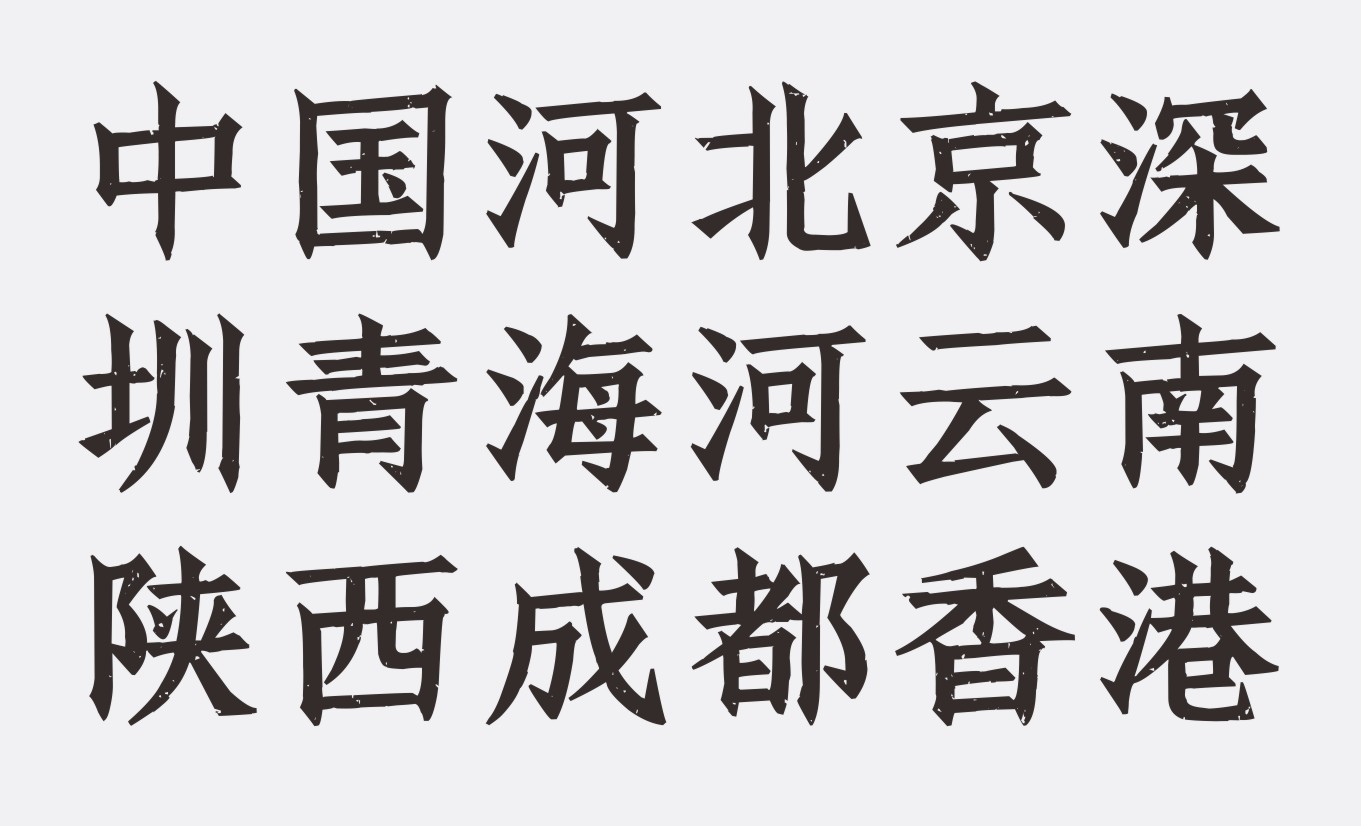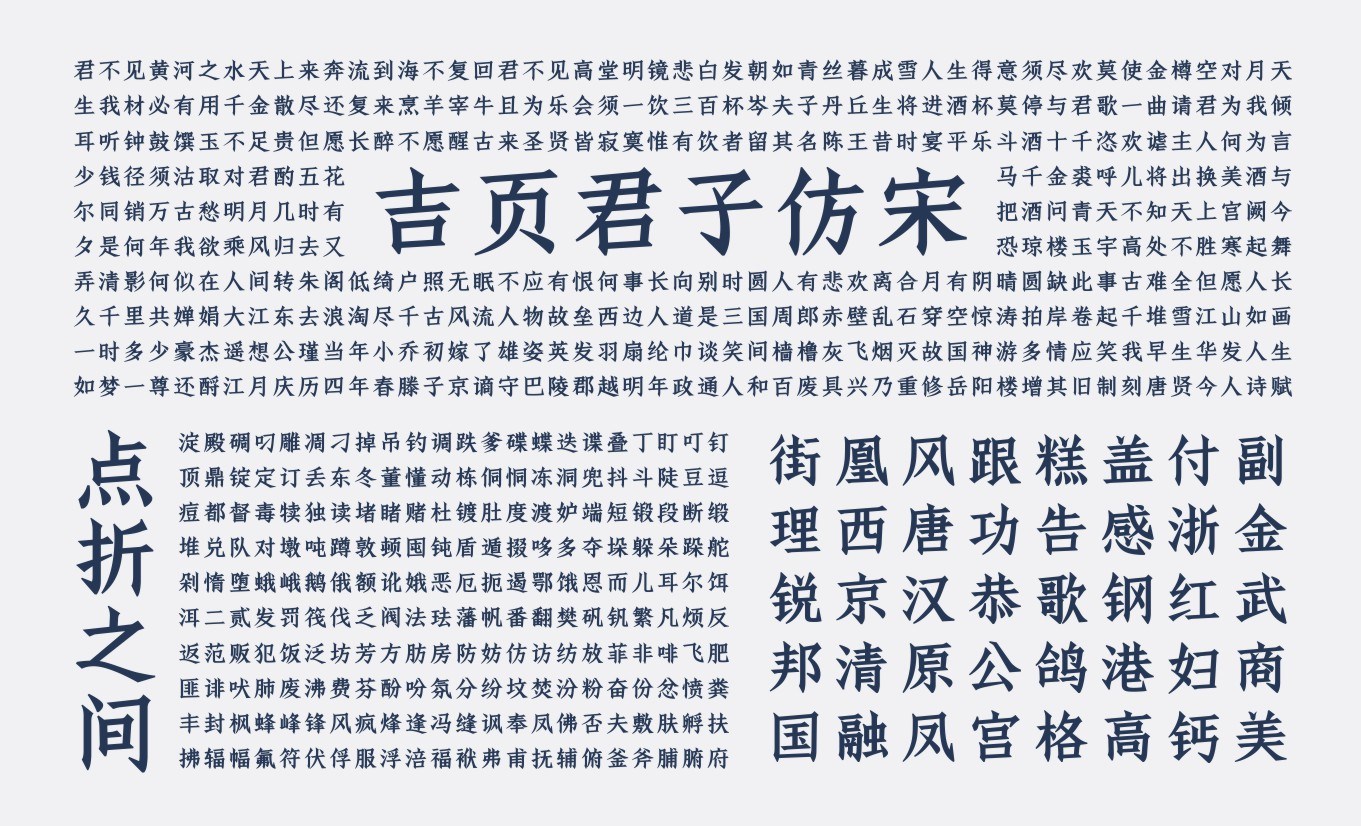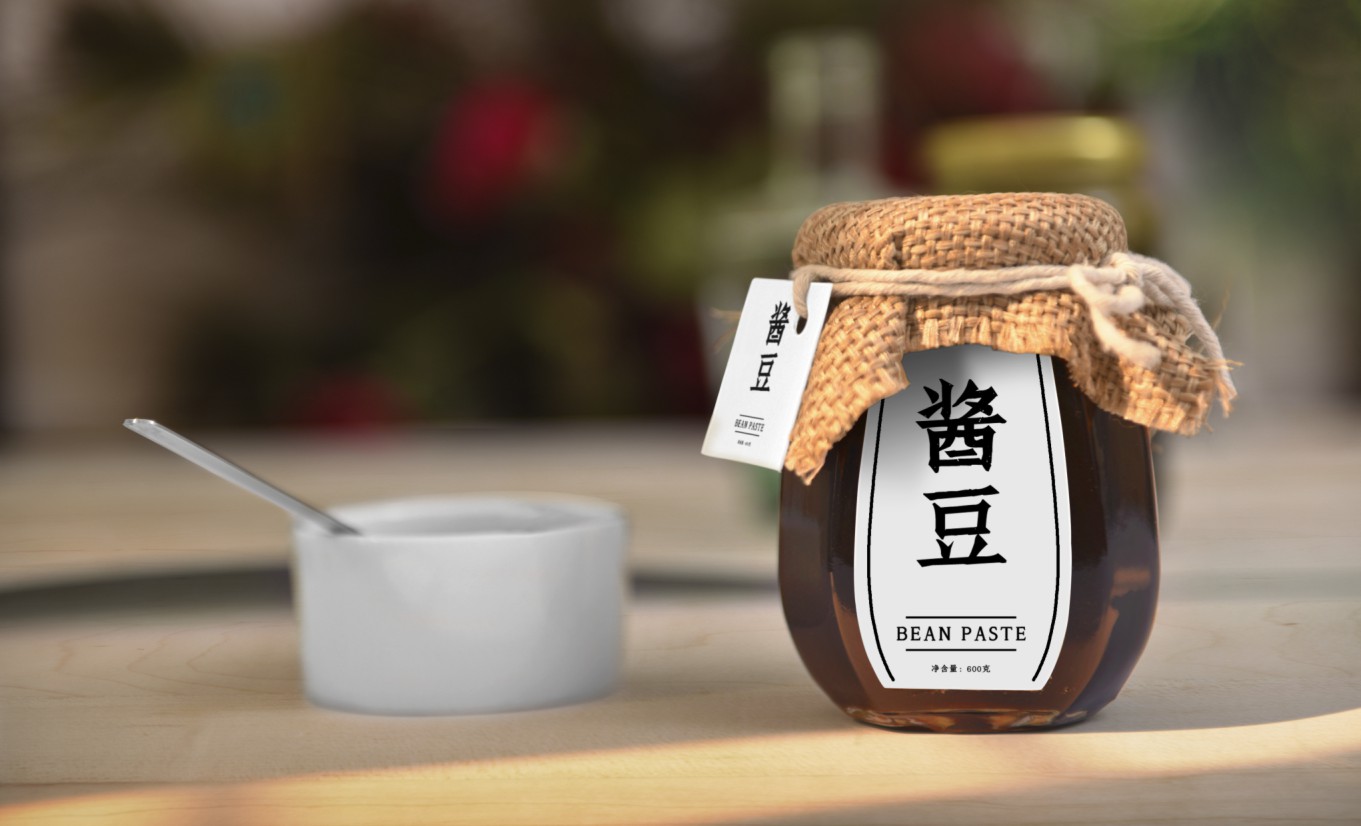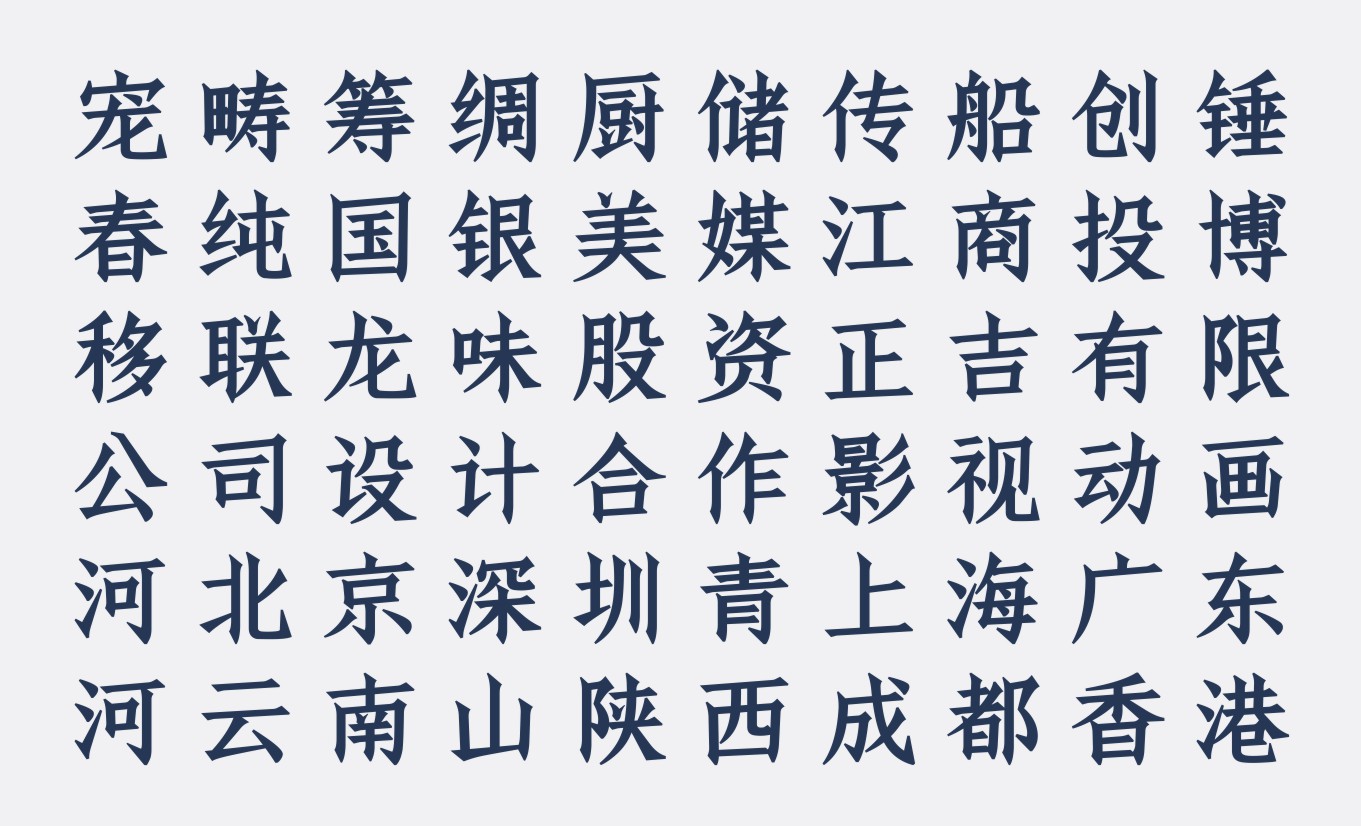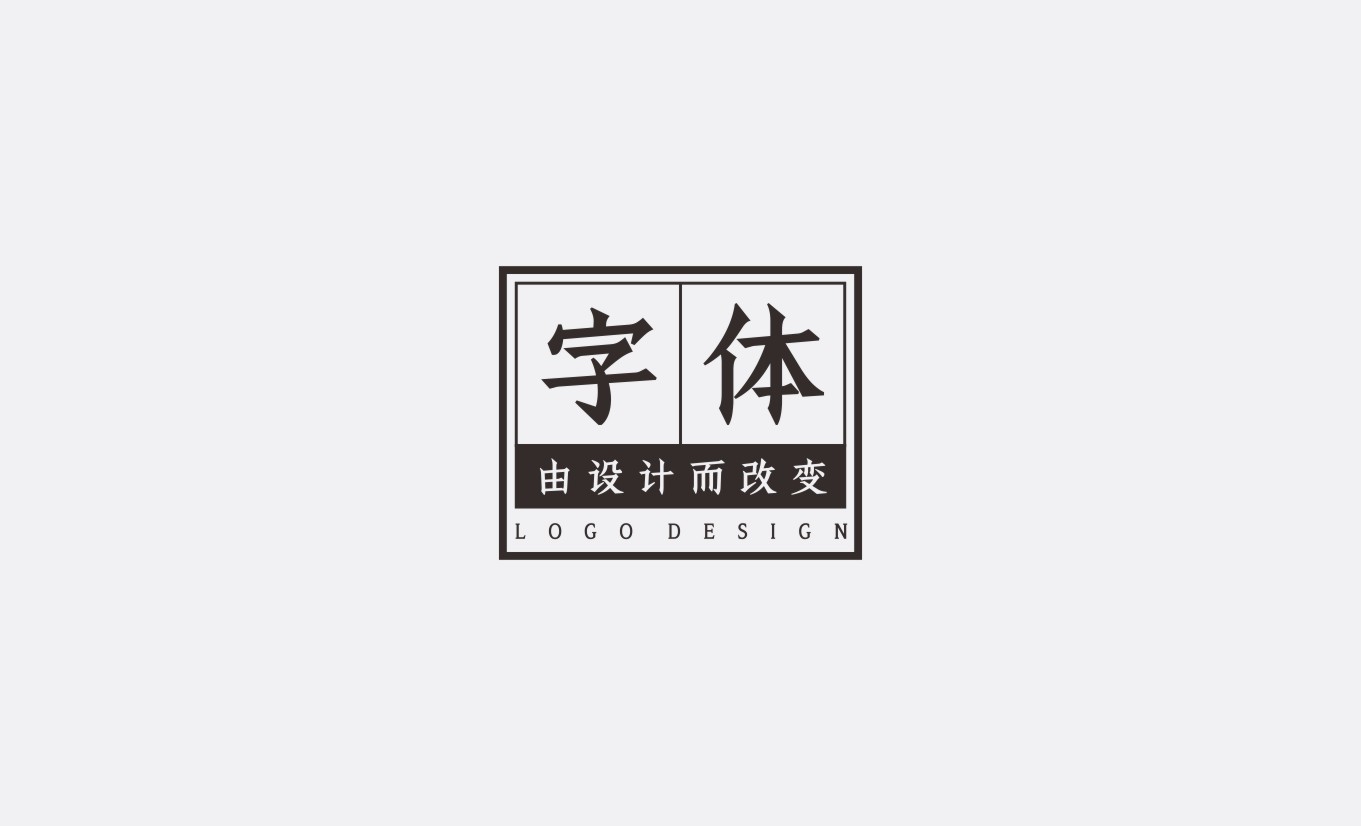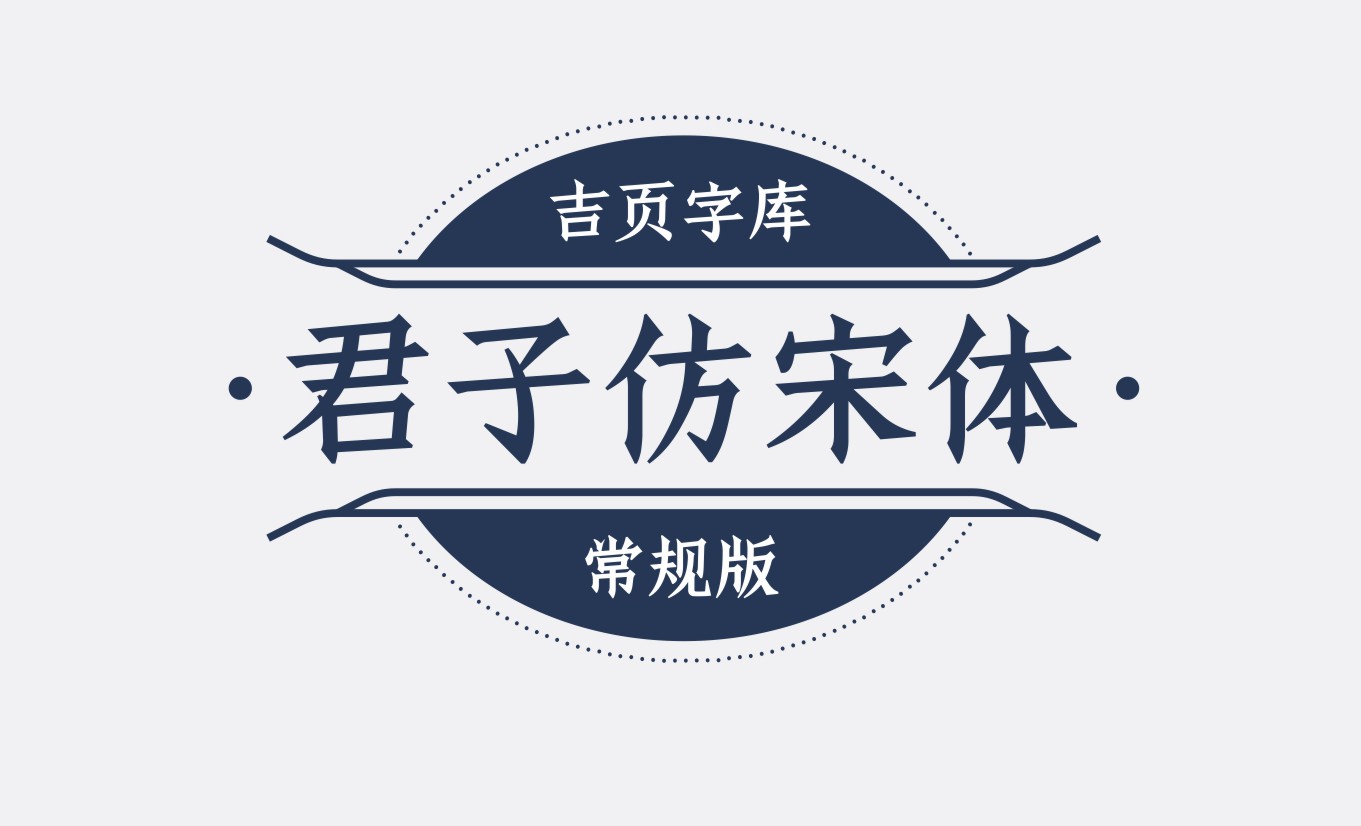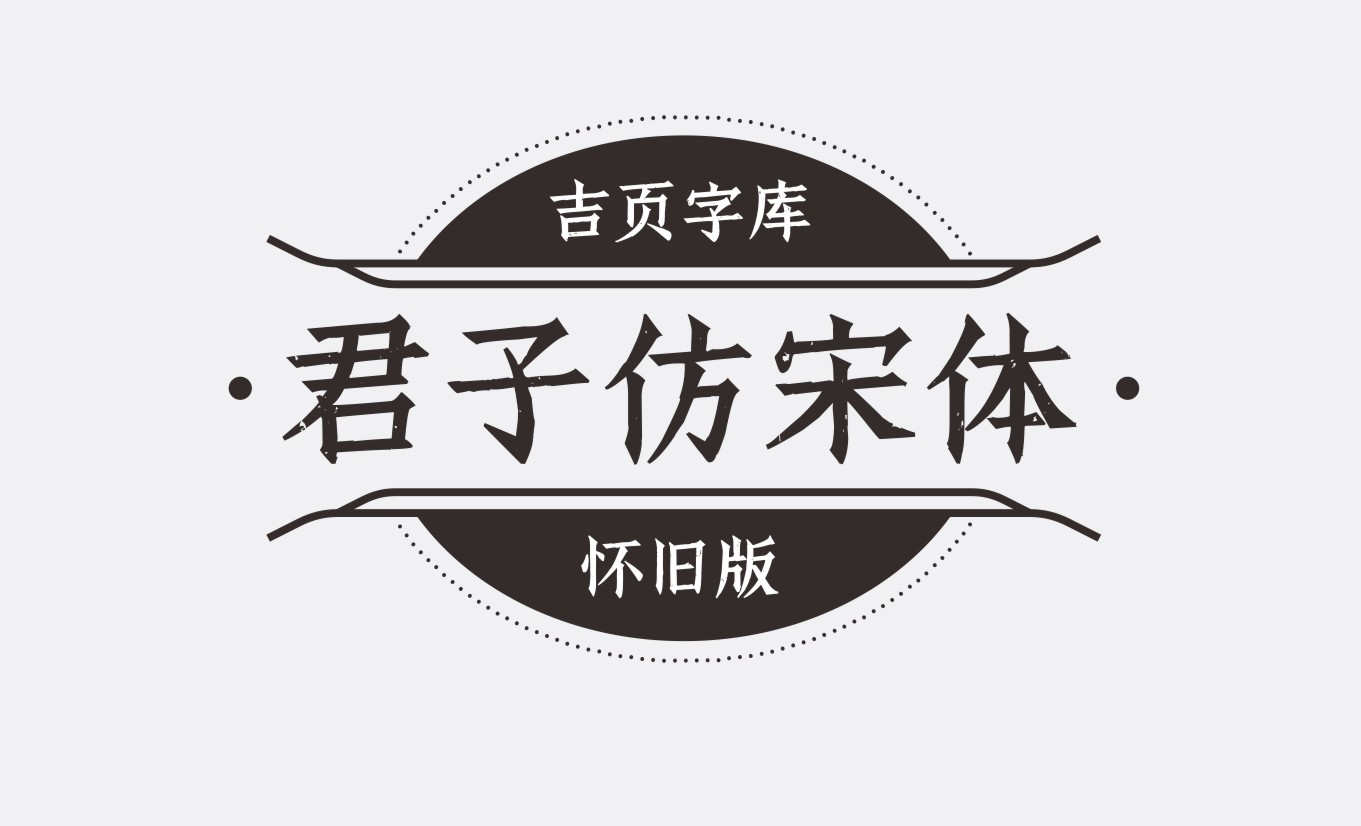
吉页君子仿宋体上线了
首先说一下为何叫“吉页君子仿宋体简”体。因为此款字体为粗仿宋,但鸡哥觉得粗仿宋这个名字较为普通,而吉页君子仿宋体在风格上没有什么浮夸的装饰性元素,笔笔坦荡,字字稳重,故视为君子。 目前市场上粗仿宋稀缺,为此,吉页字库为粗仿宋填补了一下坑。虽然是微不足道的一抹,还请各位为鸡哥点点赞,转转发。 吉页君子仿宋体简在GB2312的基础上增加了148个汉字,共计6911个汉字,大小写西文、数字及常用符号。 此外,吉页君子仿宋体简还做的一版“怀旧版”,以便不同场景的应用。
吉页君子仿宋体上线了
首先说一下为何叫“吉页君子仿宋体简”体。因为此款字体为粗仿宋,但鸡哥觉得粗仿宋这个名字较为普通,而吉页君子仿宋体在风格上没有什么浮夸的装饰性元素,笔笔坦荡,字字稳重,故视为君子。
吉页君子仿宋体简在GB2312的基础上增加了148个汉字,共计6911个汉字,大小写西文、数字及常用符号。
此外,吉页君子仿宋体简还做的一版“怀旧版”,以便不同场景的应用。